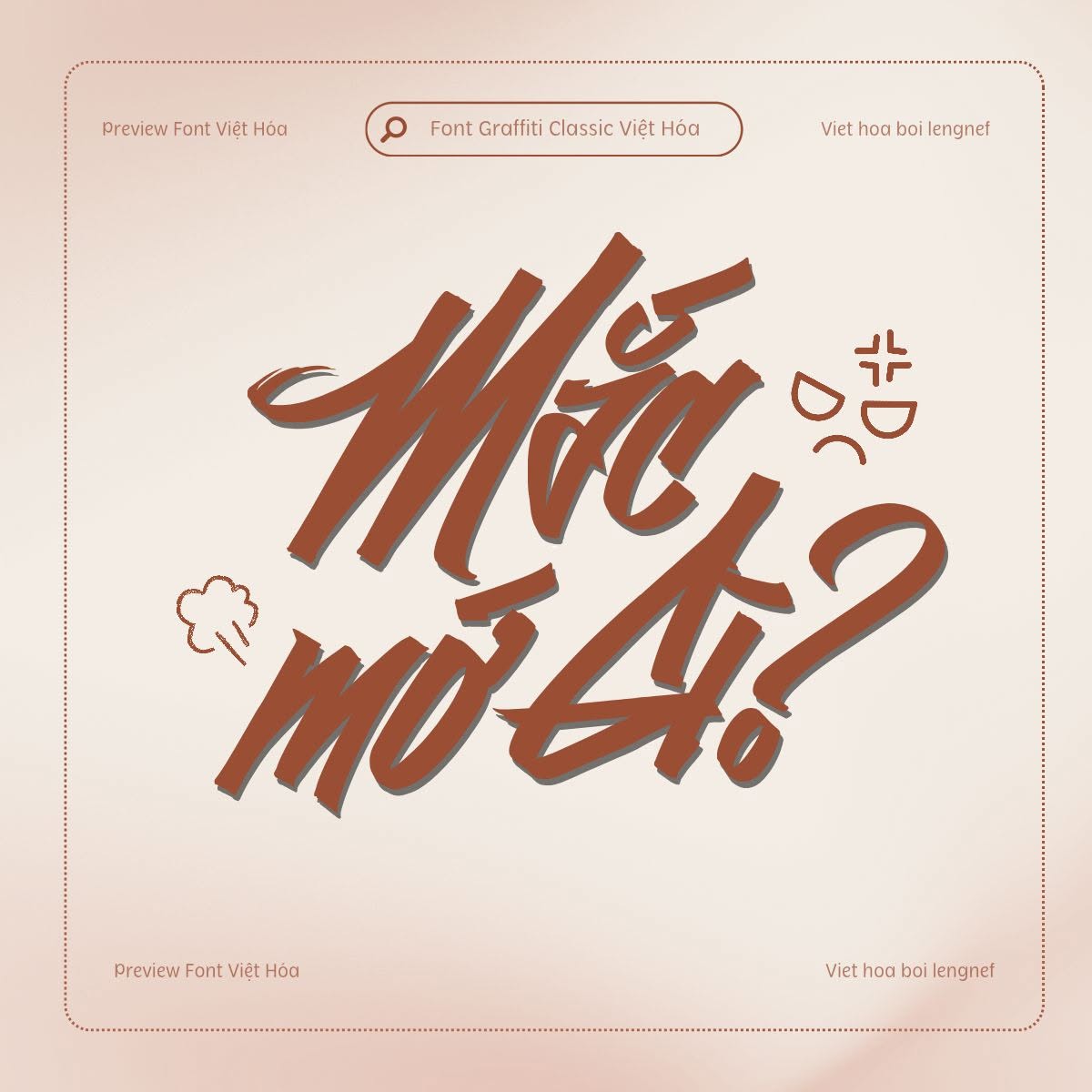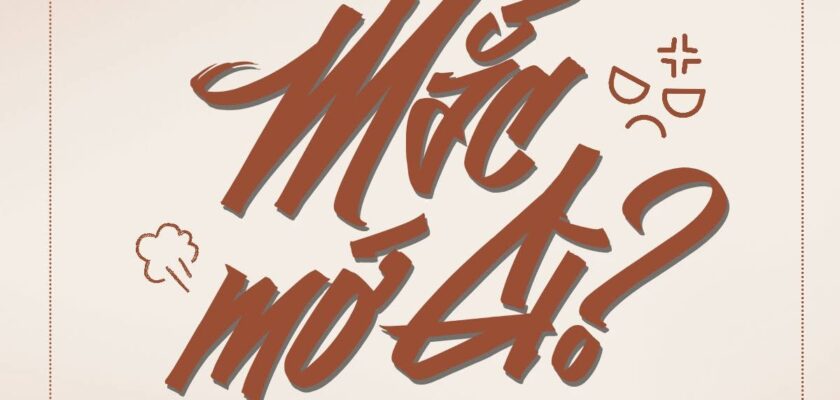
Share Font 83 || LF Graffiti Classic
- Tác giả: Robert Arnow
- Việt hóa: lengnef
Graffiti Classic là một phông chữ graffiti kết hợp nét ngẫu hứng đậm chất đường phố với sự mượt mà và đều đặn của kiểu chữ truyền thống. Phù hợp với các thiết kế đường phố, mạnh mẽ, có chất riêng, hoặc banner nhạc rock…